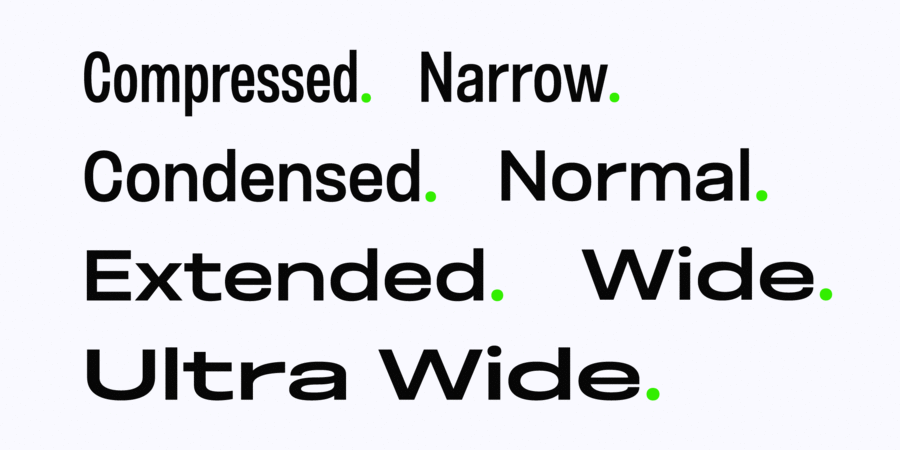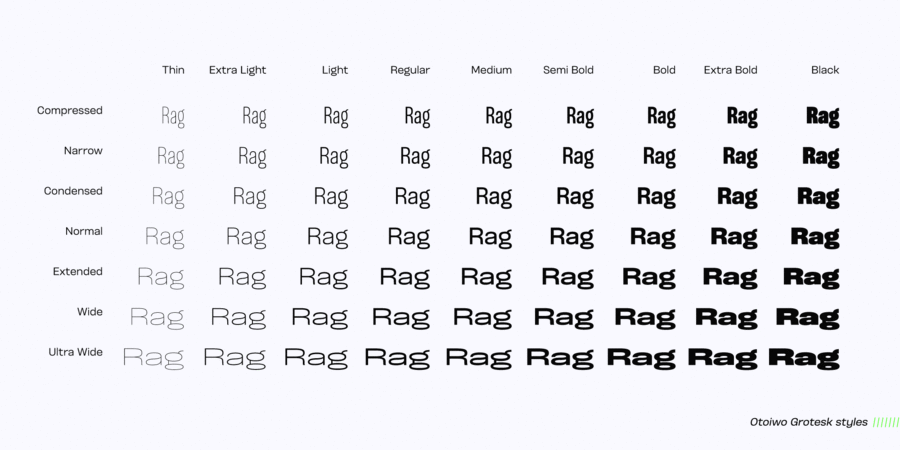
Otoiwo Grotesk (126 шрифтів)
Опис гарнітури Otoiwo Grotesk — надзвичайно універсальний шрифт без засічок із закритою апертурою. Він містить 126 стилів у 7 ширинах, кожна з яких має 9 ваг з відповідними курсивами.
Настрій сім’ї коливається від досить нейтрального в нормальній та стислій (Condensed) ширині до дуже експресивного стисненого (Compressed) та ультраширокого (Ultra Wide).
Шрифт розробив Олег Ліщук у 2023 році.
Асоціації з сімейством шрифтів Otoiwo GroteskОсобистість і характер гарнітури:
делікатний, чистий, легкий, худий, прохолодний, тонкий, сучасний, рівний, якісний, невагомий, прозорий, міський, чіткий, інтимний, крихкий, повітряний, скляний, дротяний, статичний, стрункий, високий, свіжий, практичний, економічний, зрозумілий, діловий, космополітичний, ненав'язливий, технічний, прямий, глобалізований, глобалістічний, монотонний, прагматичний, твердий, невиразний, точний, серйозний, щільний, переконливий, солідний, сильний, важливий, строковий, швидкий, наполегливий, рішучий, спортивний, чорний, потужний, суворий, кондовий, тісний, ясний, спокійний, формальний, розумний, важкий, значний, стійкий, мінімалістичний, модний, лаконічний, логічний, приємний, зручний, Простий, стандартний, впевнений, мотивуючий, помітний, яскравий, активний, амбітний, міцний, мужній, добротний, монументальний, гучний, сміливий, брутальний, надійний, індустріальний, техногенний, урбаністичний, авторитетний, крутий, залізничний, самостійний, відповідальний, західний, обов'язковий, гоночний, стабільний, швидкісний, динамічний, інженерний, креслярський, енергійний, кінематографічний, нахабний, стрімкий, різкий
дієта, гігієна, дизайн, Місто, чистота, хмарочос, кінотеатр, цигарки, бізнес, торгівля, магазин, реклама, кіно, Футбол, прапор, спорт, медицина, будматеріали, вантажоперевезення, інструмент, вантажівка, далекобійник, логістика, сейф, туалетна вода, інновації, перукарня, парфумерія, лосьйон, шампунь, суспільство, транспорт, аеропорт, метро, ліки, коворкінг, наука, хімія, фізика, вода, автобус, аптека, новини, політика, автомобіль, авто, Доставка, техніка, будівництво, ремонт, машинобудування, завод, промисловість, верстат, тренажери, екскаватор, металургія, порт, двигун, урбаністика, електростанція, енергетика, мотор, прес, вагон, залізниця, паливо, формула 1, тачки, авіація, літак, шолом, мода, одяг, небо, взуття, інженер, гонки, ралі, гра, швидкість Гарнітура асоціюється з віком: